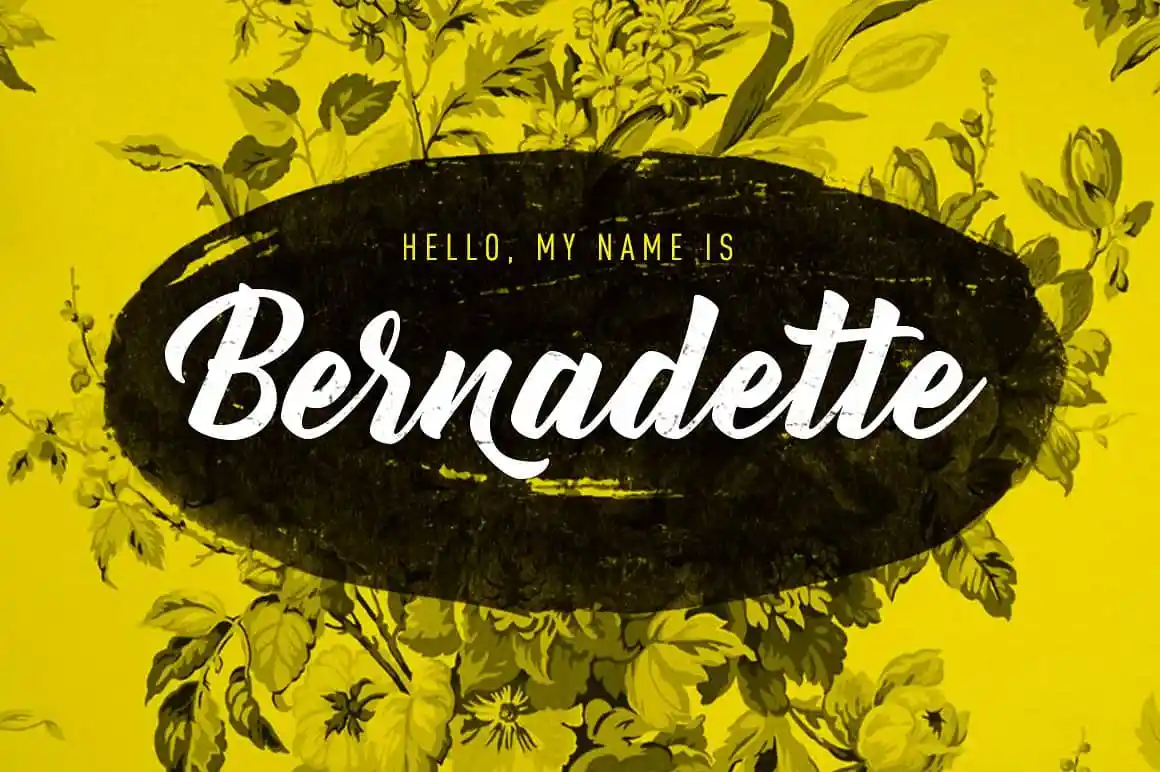
Bernadette Rough Font – Download Grátis
A Bernadette Rough Font é uma elegante seleção de traços ásperos e arredondados que irá revolucionar seu design de letra digital. Com sua tipografia feita à mão, a fonte Bernadette Rough oferece um estilo único para textos tanto grandiosos quanto sutis. Se você precisar usar os caracteres alternativos especiais, terá que acessar o painel de gílos em suas ferramentas favoritas, como Photoshop, Illustrator ou InDesign. Essa fonte é uma escolha perfeita para quem valoriza um design único e atemporal. Sempre surpreendente com seu toque moderno na caligrafia tradicional, Bernadette Rough é a escolha certa para qualquer designer gráfico que busca algo autêntico e de alta qualidade em suas criações digitais.